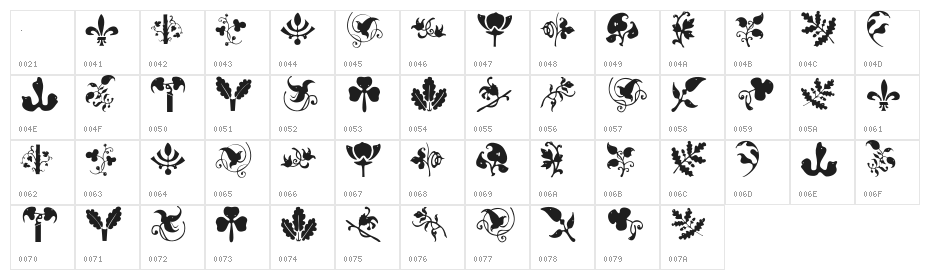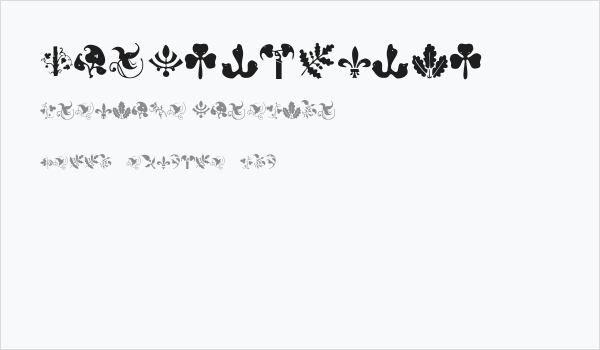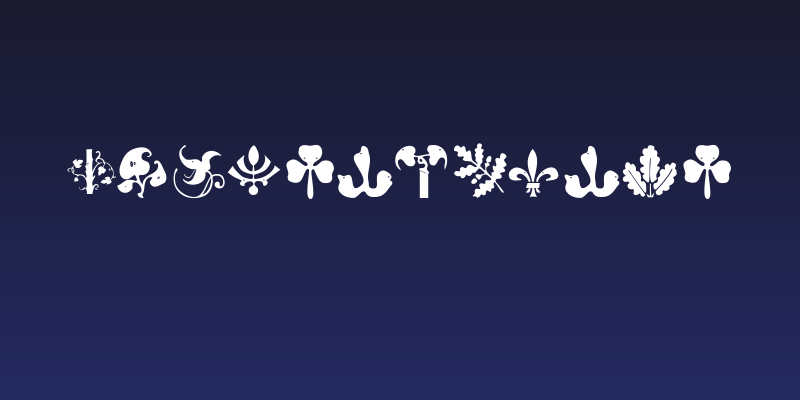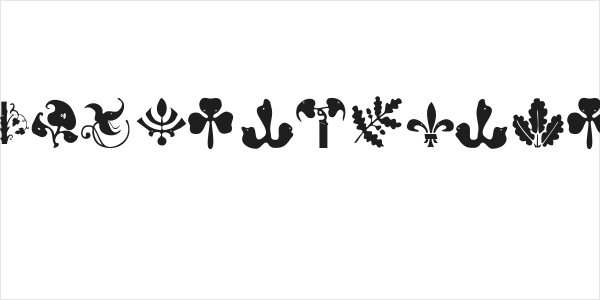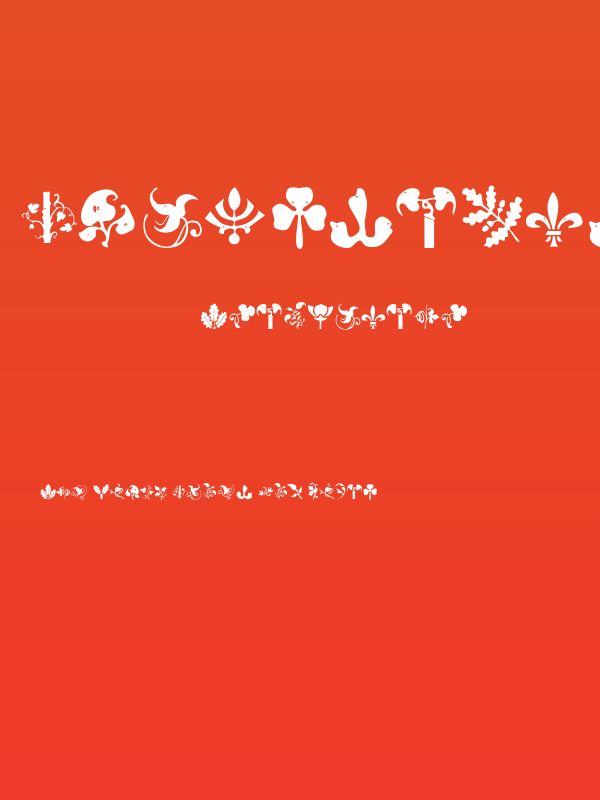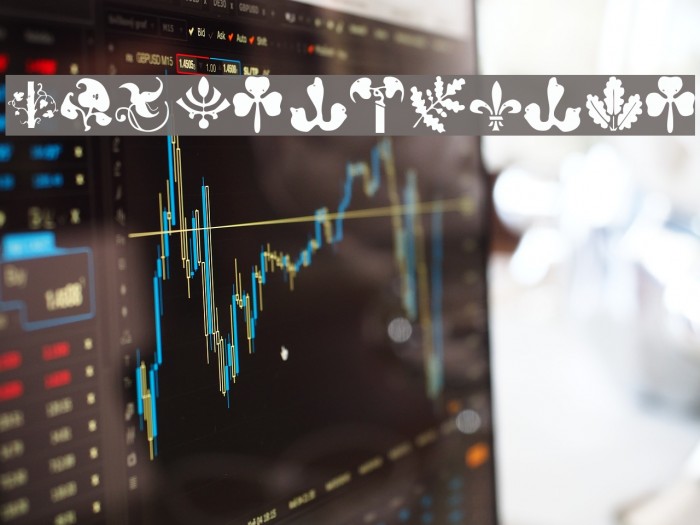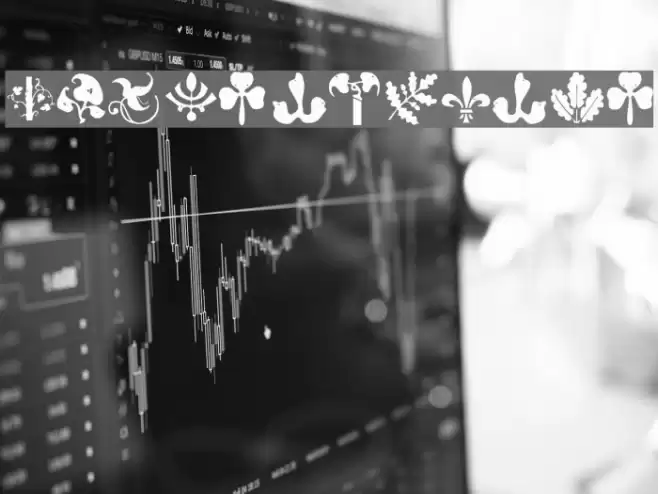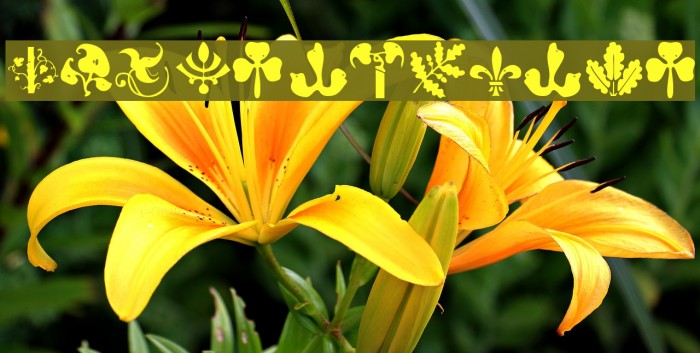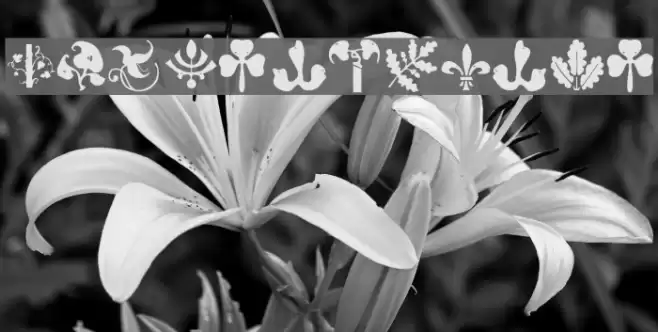
BirdsNPlants Font
| Style général | Decorative, Ornamental, Nature-inspired |
| Cas d'utilisation | Borders, embellishments, icons, and decorative accents. |
| Projets proposés | Invitations, greeting cards, scrapbooking, decorative borders, nature-themed branding, and ornamental dividers. |